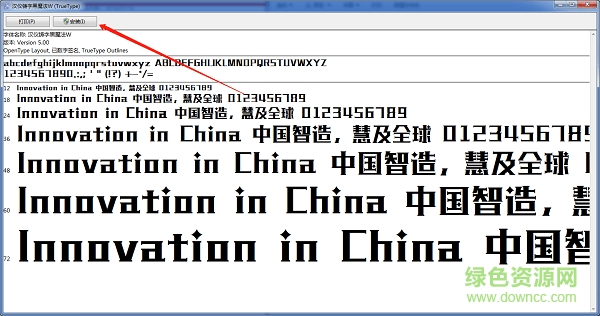
漢儀鑄字黑魔法體字體渾厚粗壯,剛勁有力,會(huì)使字面看起來(lái)比較的醒目,因此比較適用于標(biāo)題以及其他一些比較醒目的字段,喜歡的用戶可來(lái)綠色字資源網(wǎng)下載哦!
漢儀鑄字黑魔法體是漢儀字庫(kù)設(shè)計(jì)的一款非常個(gè)性的字體,這款字體有棱有角,每一個(gè)筆畫(huà)都很直,有著較強(qiáng)的力量感,也很穩(wěn)重,同時(shí),筆畫(huà)的兩端都帶有延伸,為字體增加了個(gè)性,非常的帥氣,不僅支持漢字,也支持英語(yǔ)和數(shù)字,為各位設(shè)計(jì)師又增加了一個(gè)字體選擇!
1、支持中文簡(jiǎn)體和繁體。
2、支持網(wǎng)絡(luò)常用中文簡(jiǎn)繁。
3、支持西文和數(shù)字。
4、字體風(fēng)格:簡(jiǎn)約、現(xiàn)代、國(guó)際化、時(shí)尚、有力、堅(jiān)硬、帥氣、休閑。
5、推薦場(chǎng)景:標(biāo)志、導(dǎo)視、廣告、游戲、動(dòng)漫、影視、包裝。